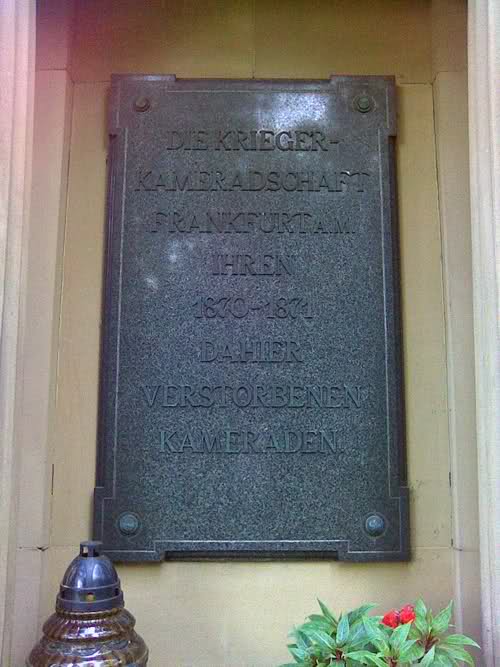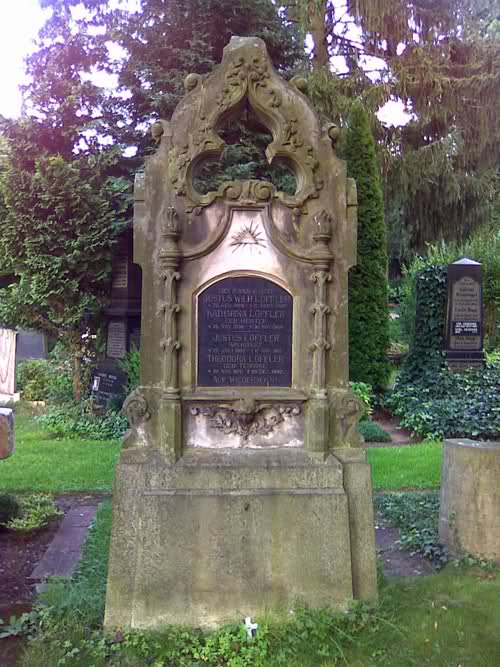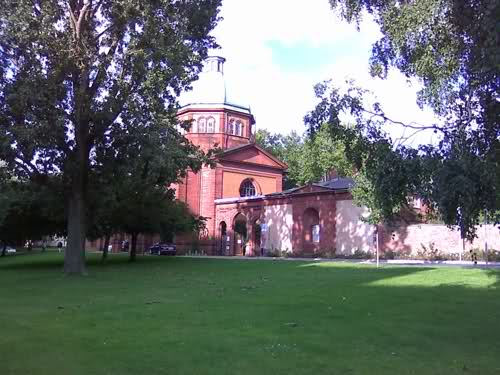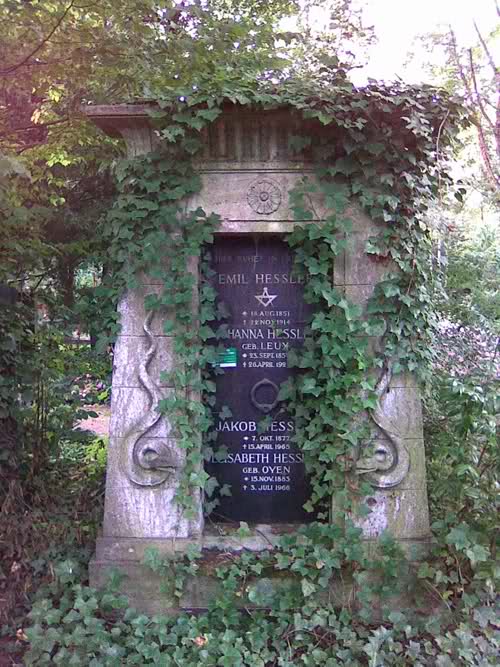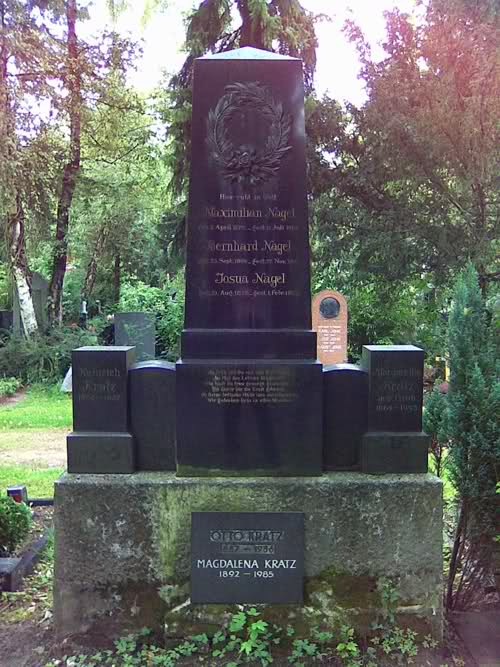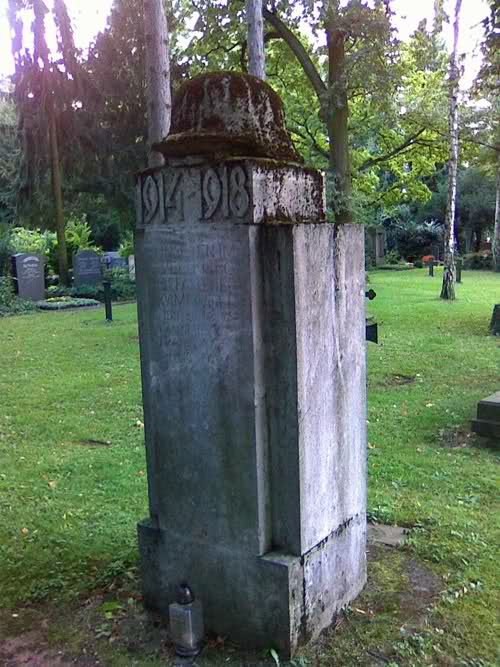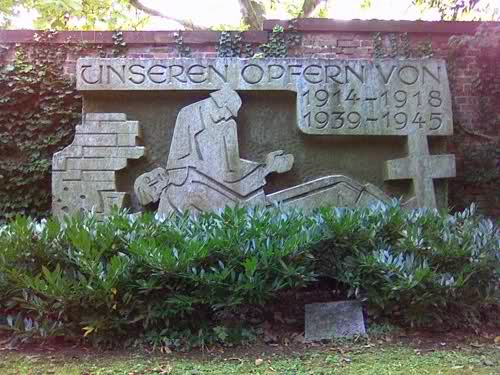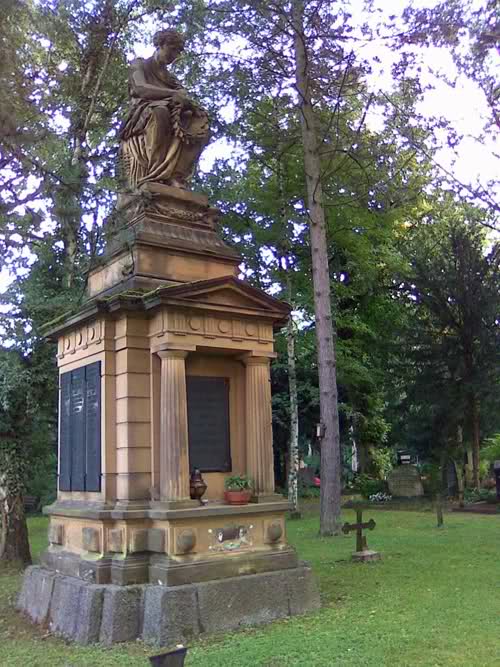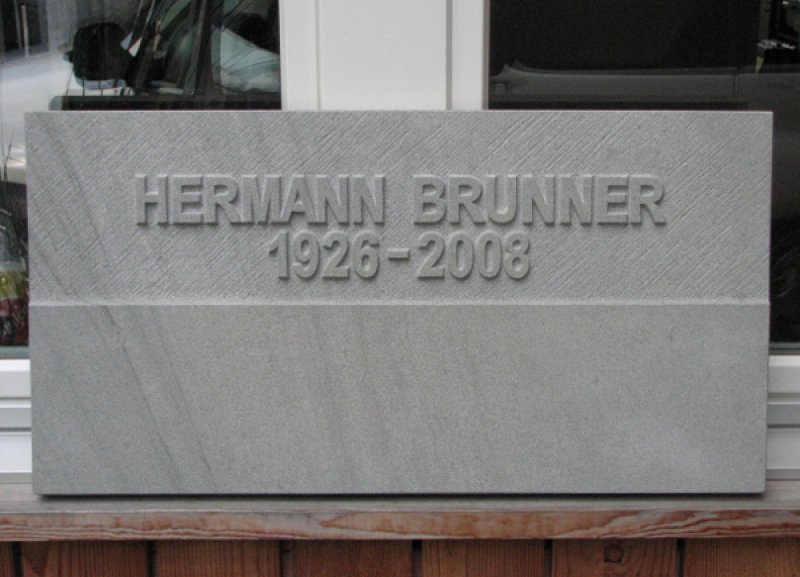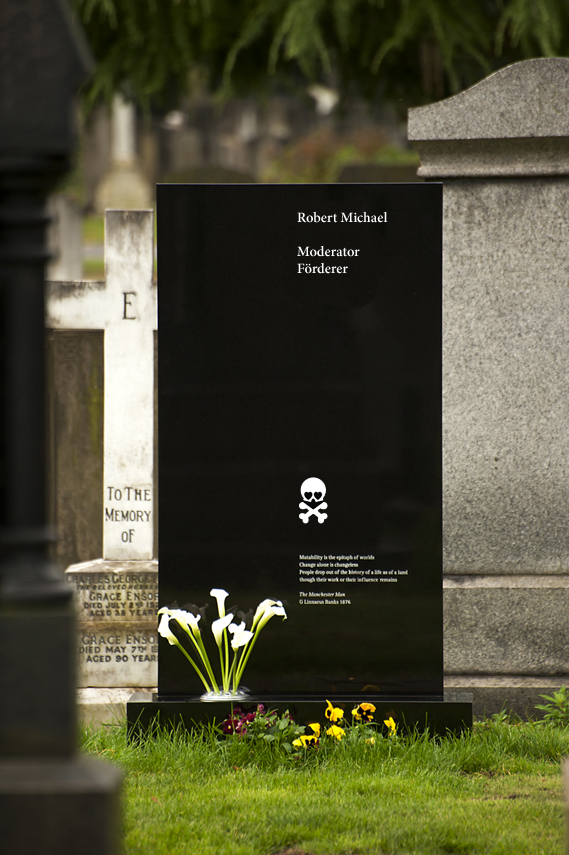
Tombstone-Spotter
So, damit der verehrte Kollege Pachulke nicht länger scharren muss, starte ich mal wie versprochen den Tombstone-Spotter-Thread.
Ich habe eben mal einen Ausflug auf den Hauptfriedhof in Neu-Isenburg unternommen. Wahnsinnig prickelnd ist das Ergebnis nicht; ich habe nur Steine nach 1900 gefunden, anscheinend gab es vorher einen anderen Friedhof... Und ich habe lediglich attraktivere oder sonstwie bemerkenswerte Exemplare abgelichtet - über Grabsteine müssen wir ja nicht unbedingt Hohn und Spott ausgießen :D Mein hauptsächliches Fazit aus dieser Exkursion: Zumindest nach 1900 war auch in der Steinmetzkunst das sperren von Versalien nicht übermäßig verbreitet...
Mini 001: Ist mir einfach als schlicht und geschmackvoll aufgefallen.
Mini 002: Ganz interessant gemacht; besteht aus zwei Steinen zwischen denen eine dünne Metallplatte eingesetzt ist, aus der Buchstaben ausgefräst wurden.
Mini 003: Eines der seltenen Exemplare mit gesperrten Versalien; leider unter besonders schlechten Lichtverhältnissen entstanden...
Mini 004: Eine besonders schöne Gebrochene :D
Mini 005: Hier hat man sich ebenfalls die Mühe gemacht, zu sperren.
Mini 006 & 007: Denkmal.
Mini 008, 009, 010 & 011: Noch ein Denkmal. Die Germania, stand ursprünglich genau in der Mitte der Altstadt, mit Blickrichtung Paris...
Mini 012: Eines der ungewöhnlicheren Exemplare; geht über das übliche »rechteckig und gut so« hinaus.
Mini 013: Was könnte das sein? Ähnelt dem Pour le Mérite, aber mit dem Vogel drunter...?
Mini 014 & 015: Den Opfern eines Explosionsunglücks...
Mini 016: ...und auf der Rückseite den Opfern eines Gasunglücks...
Mini 017 & 018: ...und dahinter ein Kriegerdenkmal.
Mini 019: Auf diesem Friedhof das einzige Exemplar mit den Gesichtern der Verstorbenen.
Mini 020 & 021: Eines der wenigen älteren Exemplare, altmodisch und hübsch, insbesondere das gemeine g.
Mini 022: Noch ein älteres Exemplar, wieder ein schönes g :D
Mini 023: Schöne altmodische Schrift.
Mini 024: Und nochmal eine schöne Gebrochene :D
Kannst du die kleinen mit größeren Bildern verlinken? Oft erkennt man fast nichts von der Schrift.
Ach wie cool, das wird ein spannender Thread! Ich bin zur Zeit im Ausland unterwegs, aber im Oktober bin ich wieder in Hamburg, dann kann ich Spannendes vom Ohlsdorfer Friedhof beitragen, versprochen!
Hier auf der spanischen Insel, wo ich gerade bin, werden die Toten nicht in der Erde bestattet, sondern in der Regel in so einer Art „Schließfach“, ich meine, in so steinernen Fächern übereinander und oberhalb der Erde. Und noch eine Besonderheit gibt es: Es scheint hier Sitte zu sein, auf eine runde Porzellanplatte das Konterfei der Verstorbenen zu drucken und am Grabfach zu befestigen. Das mutet manchmal ganz bizarr an, wenn es sich um das gemeinsame Grab eines Ehepaares handelt, bei dem ein Partner sehr jung verstorben ist und der andere steinalt. Auf der gemeinsamen Porzellanplatte schaut uns dann ein Jüngling an, der neben einer ganz alten Dame abgebildet ist, oder umgekehrt. Man bekommt gedanklich kaum zusammen, dass die beiden mal verheiratet waren.
Ein sehr aktuelles Beispiel (im www gefunden):
brunner_klein.jpg[/attachment:3ma42ozd]Ich dachte nicht dass selbst die Arial für einen Stein geeignet ist, bin aber von Ergebnis sehr angetan.
Kannst du die kleinen mit größeren Bildern verlinken? Oft erkennt man fast nichts von der Schrift.
Ein sehr aktuelles Beispiel (im www gefunden):
brunner_klein.jpg[/attachment:7340bwte]Ich dachte nicht dass selbst die Arial für einen Stein geeignet ist, bin aber von Ergebnis sehr angetan.
Cool... Hätte gesperrt sein dürfen (...), aber sieht wirklich erstaunlich gut aus :D
Es scheint hier Sitte zu sein, auf eine runde Porzellanplatte das Konterfei der Verstorbenen zu drucken und am Grabfach zu befestigen.
Schlimm finde ich, dass man an einigen Steinen Fotos sieht... Das ist irgendwie gruselig bis geschmacklos... :neenee:
Der ist vom Johannisfriedhof Leipzig, man beachte den ſs-Verbund und das ä:
Der ist vielleicht auch vom Johannisfriedhof, vielleicht aber auch von wo ganz anders her, habe ich leider vergessen und unter »Sonstiges« abgelegt gehabt, so daß ich das nicht mehr zuordnen kann: